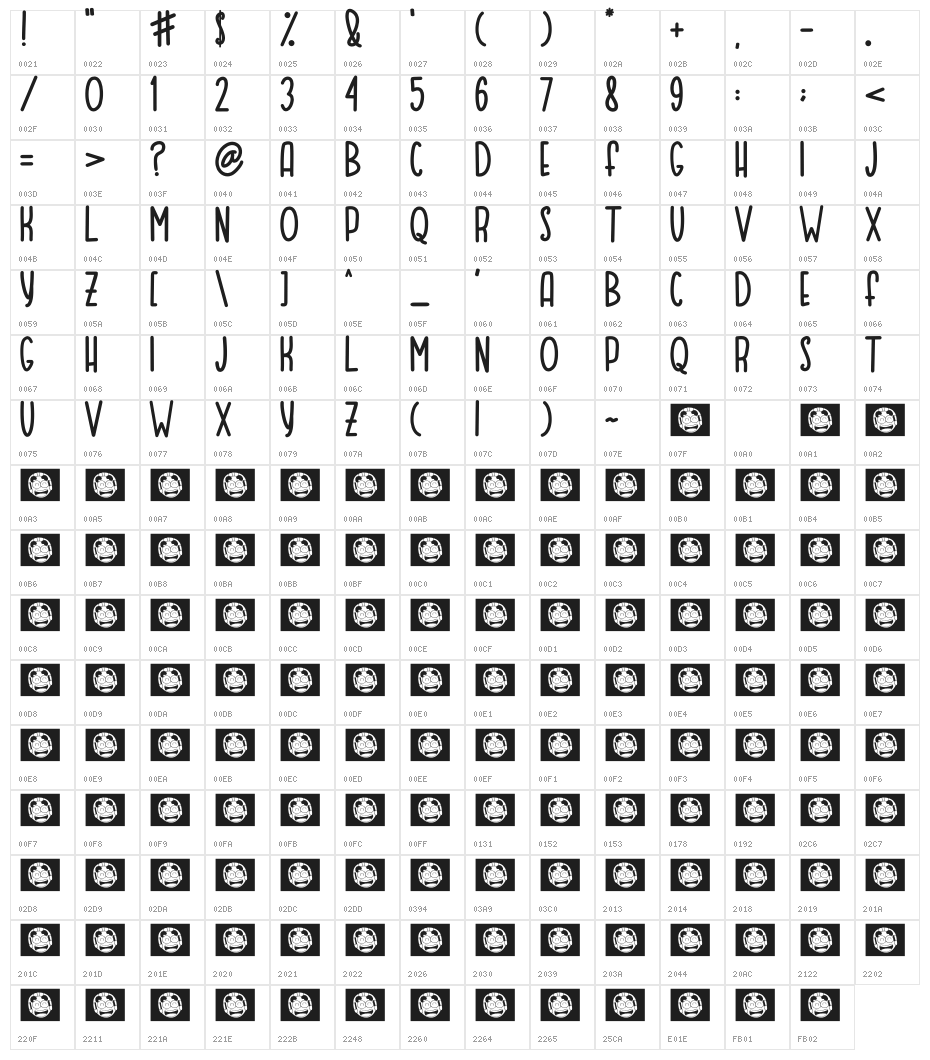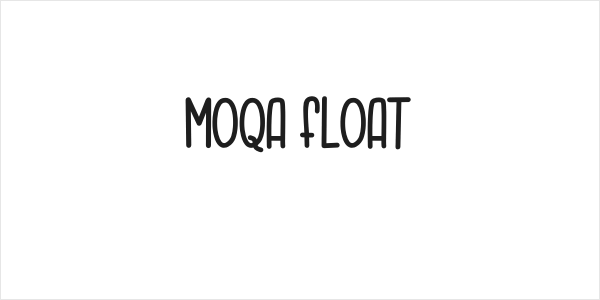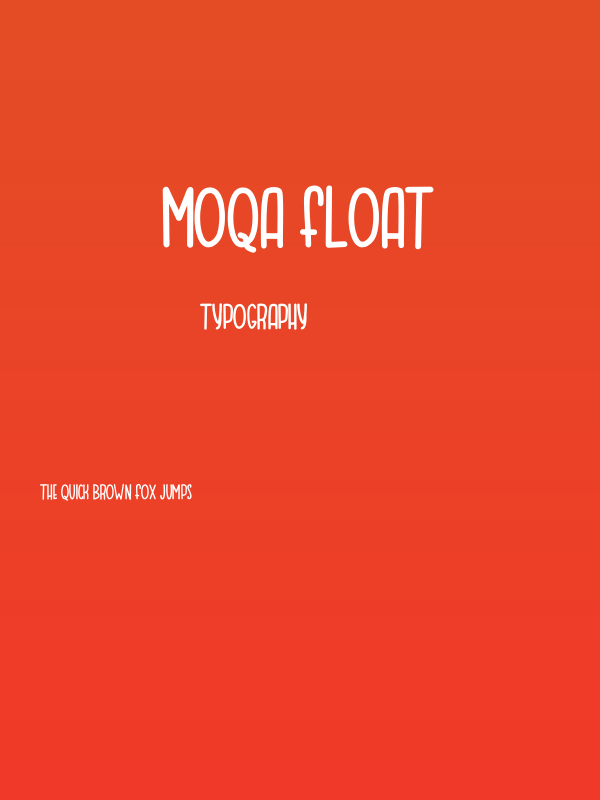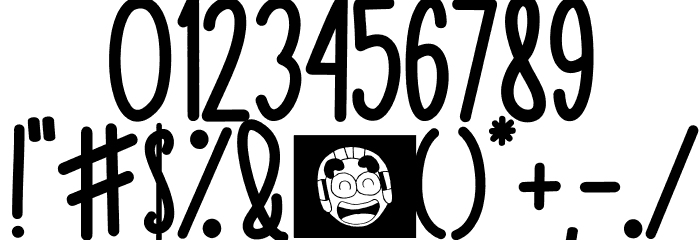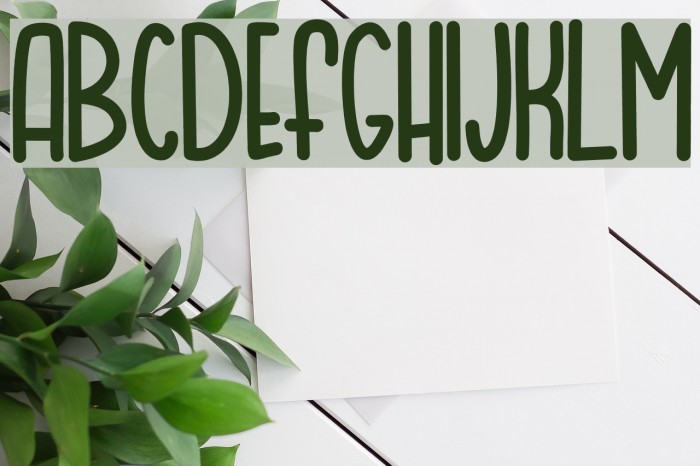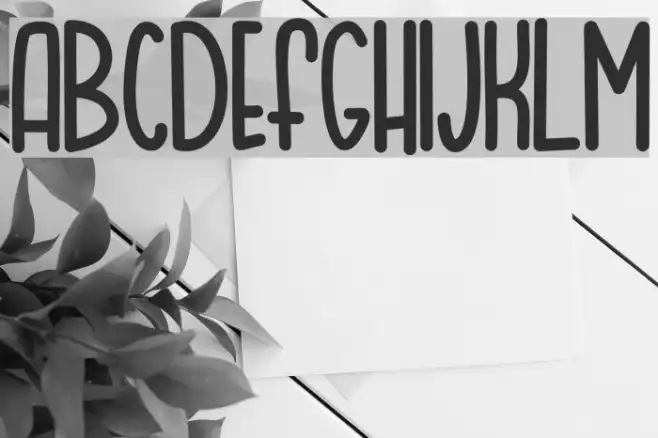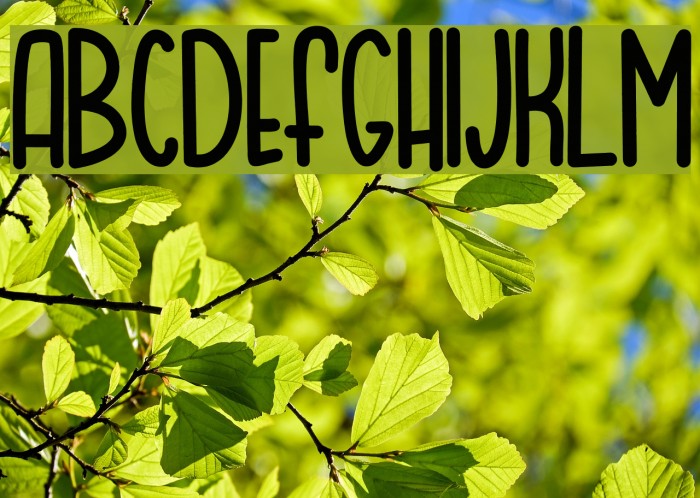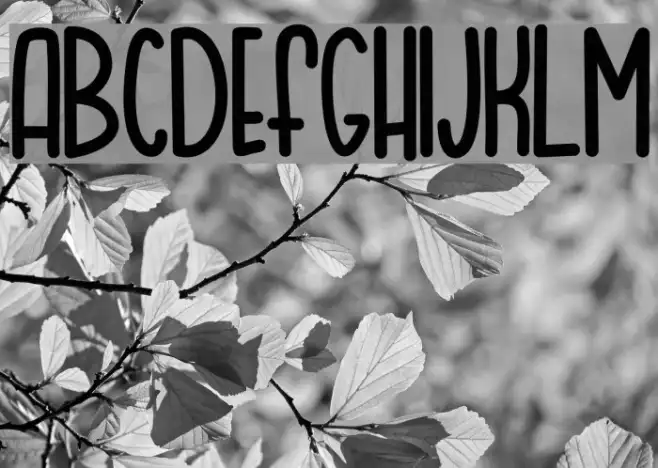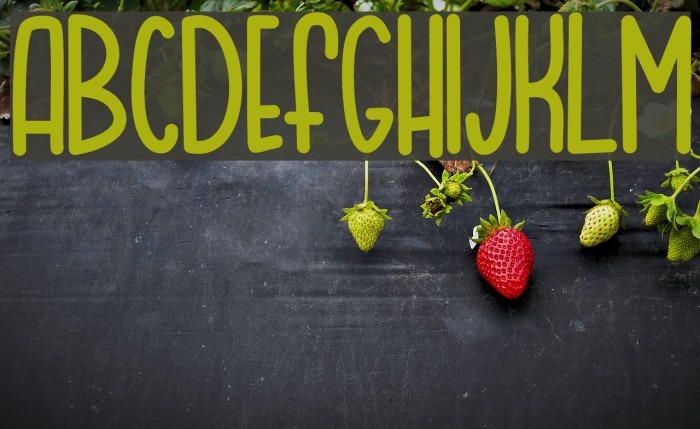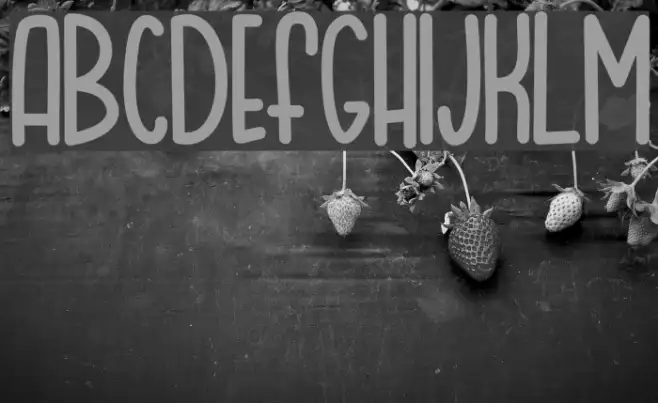
MOQA FLOAT Font
| Estilo general | Playful, Whimsical |
| Proyectos propuestos | Ideal for children's books, playful branding, posters, and creative social media graphics. |